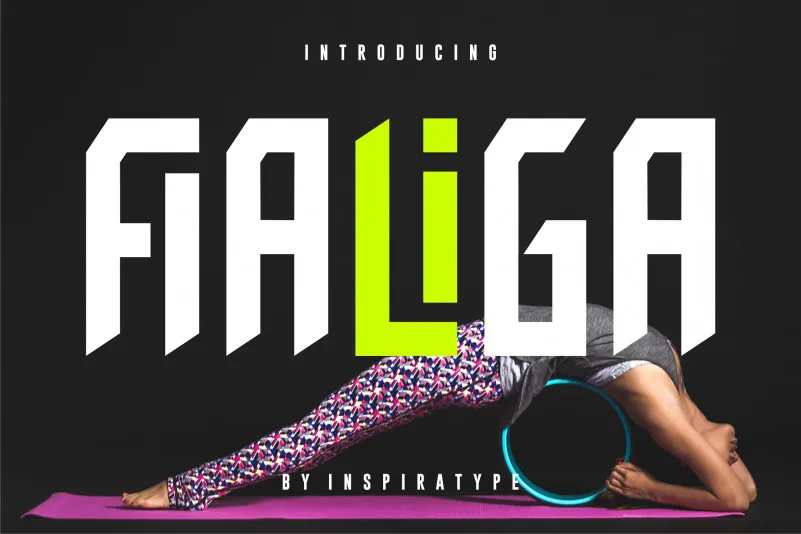
Fialiga Display Font – Fonte Grátis
Fialiga Display Font
A Fialiga Display Font é uma tipografia com aparência artística e moderna, criada a mão inspirada nos clássicos cartazes dos anos 50 e 60. Esta fonte traz uma vasta variedade de alternativas de ligação de tipo aberto, tanto para letras maiúsculas quanto minúsculas, números e sinais de pontuação, oferecendo inúmeras variações em cada caractere. Além disso, inclui ganchos elaborados que permitem ao designer personalizar seu trabalho de design. Ideal para uso em logotipos, cartões de visita, posters, desenho de roupas e etiquetas, essa fonte atende às necessidades do design gráfico moderno. Inspirada no estilo dos clássicos cartazes, a Fialiga Display Font oferece um toque único para seus projetos digitais.